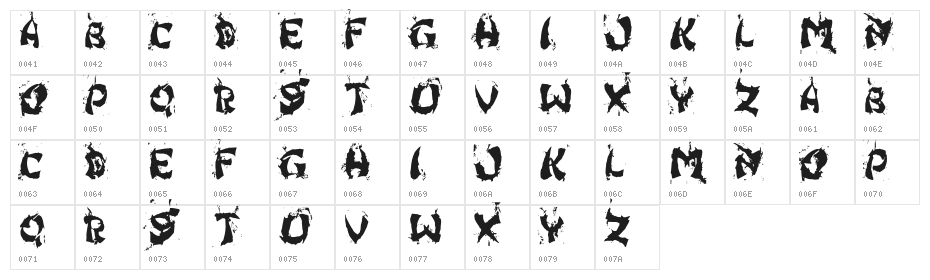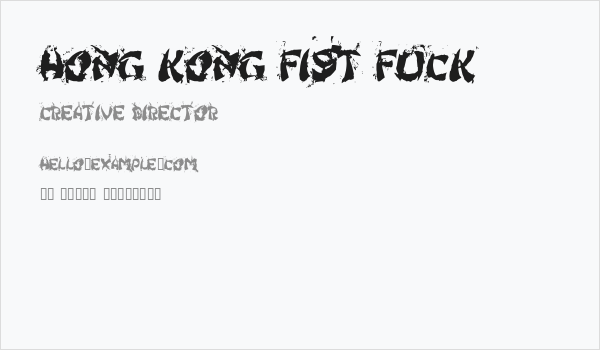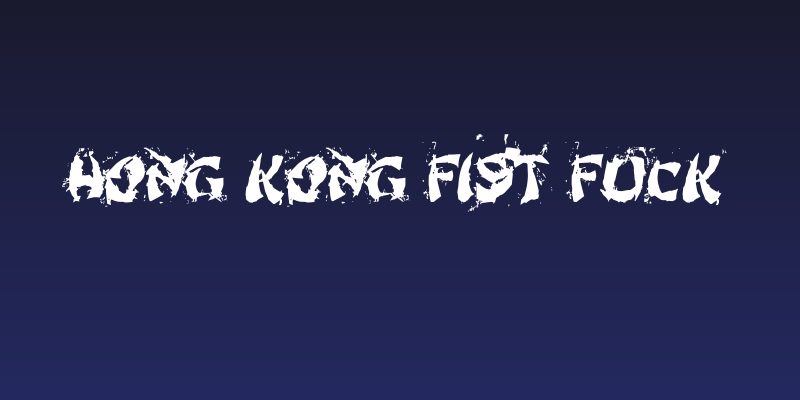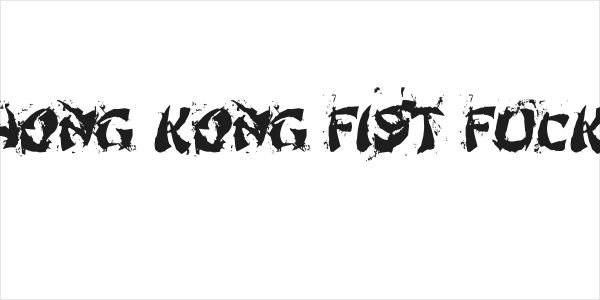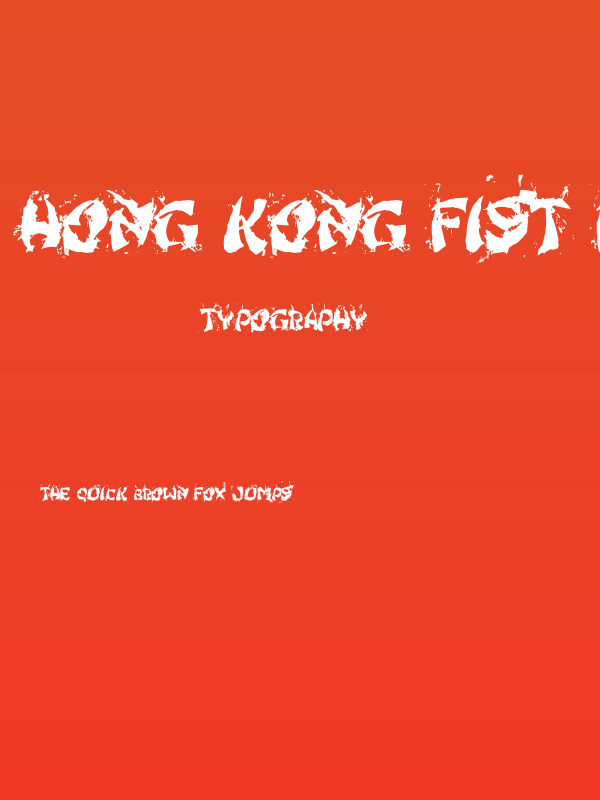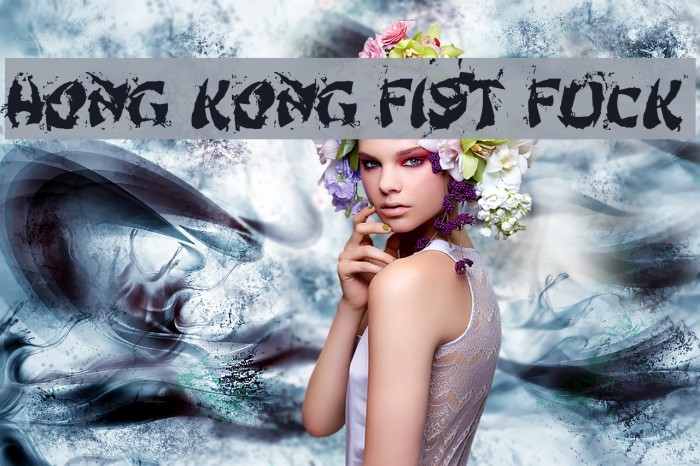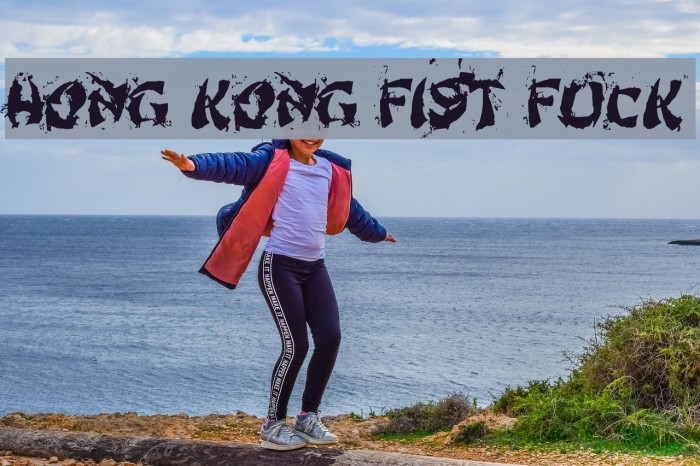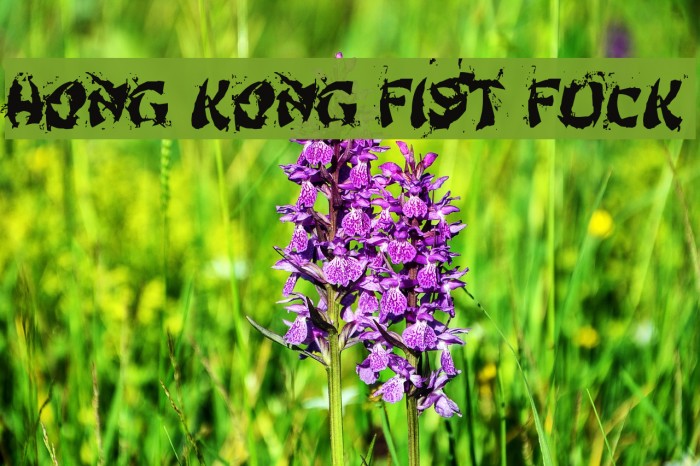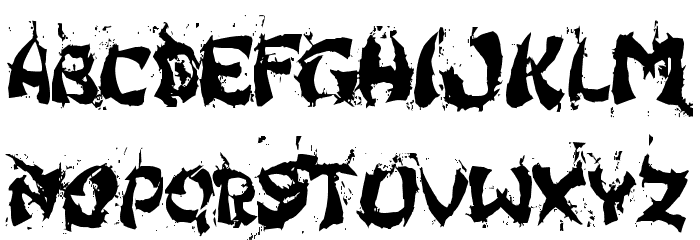
Hong Kong Fist Fuck Font
| Gesamtstil | Grunge, Urban, Edgy |
| Anwendungsfall | Logos, Posters, Headlines |
| Vorgeschlagene Projekte | Ideal for music album covers, streetwear branding, event posters, or any project seeking an edgy, rebellious vibe. |